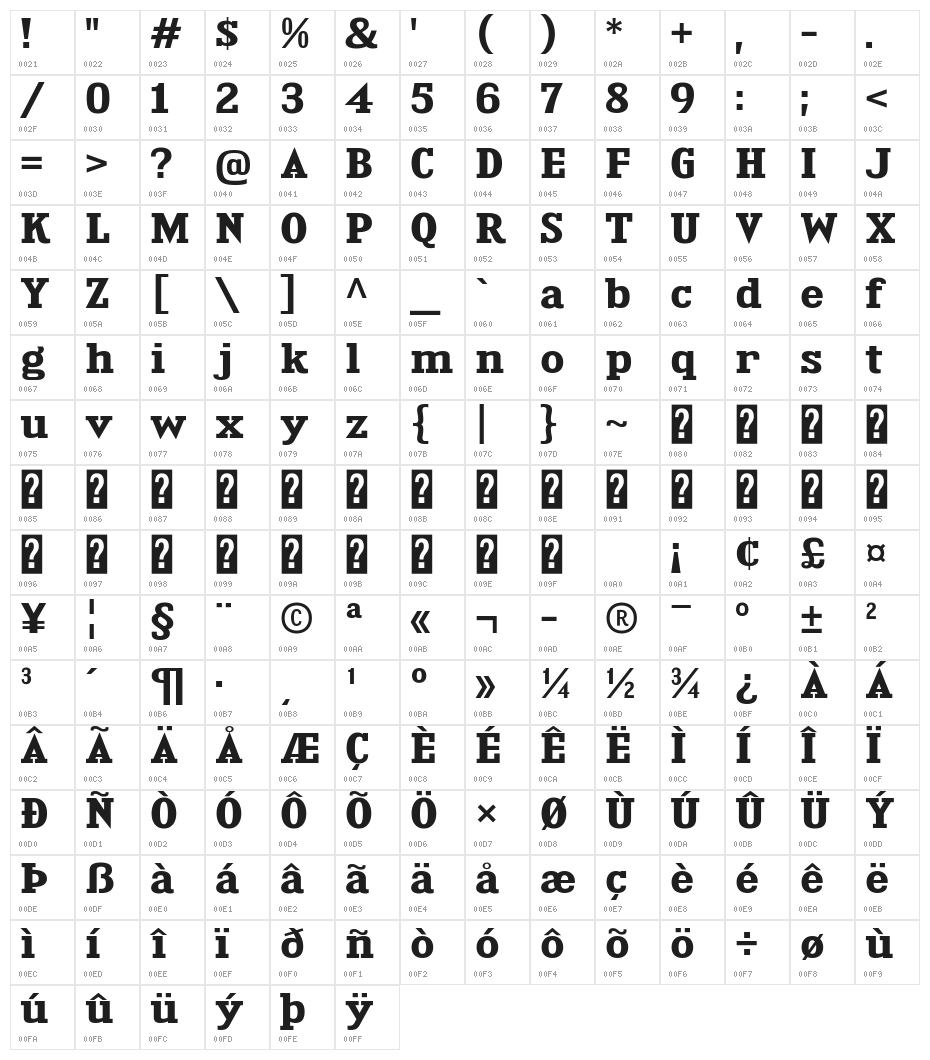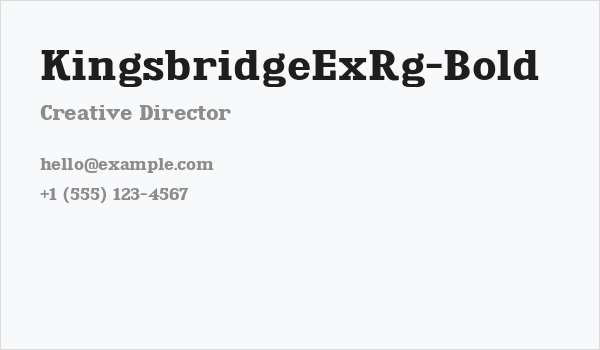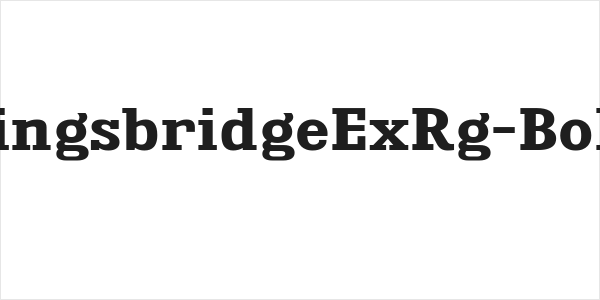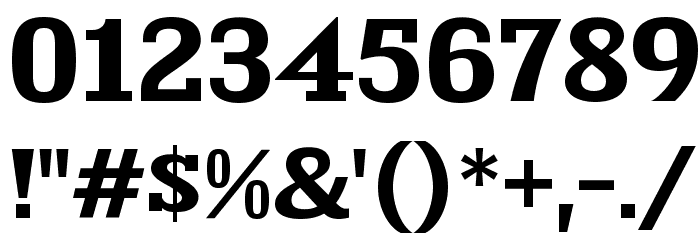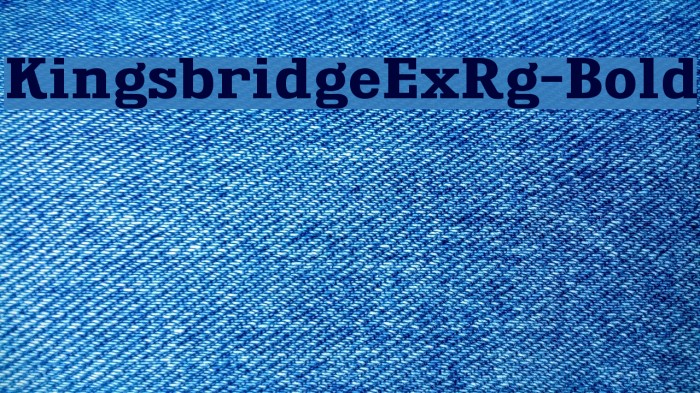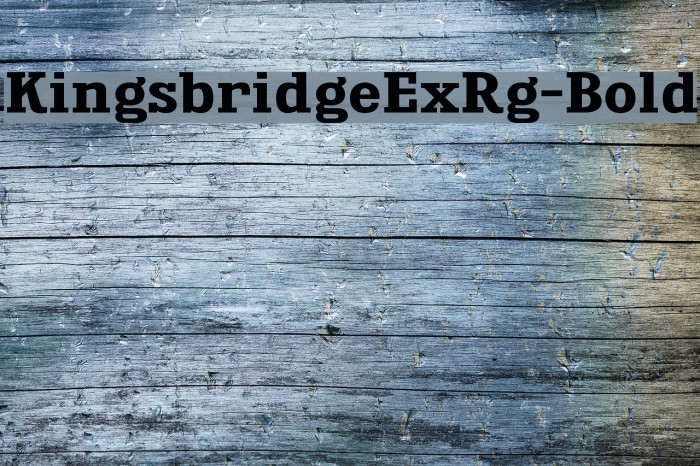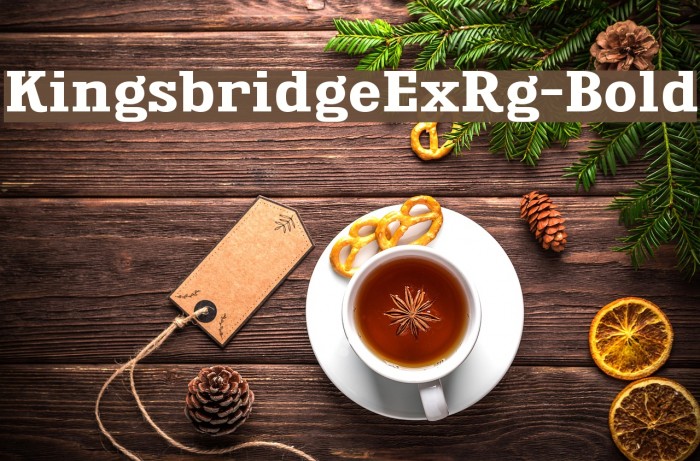
KingsbridgeExRg-Bold Font
✎ Serif
Fonts by Typodermic Fonts
| Caso de uso | Headlines, Logos, Branding |
| Proyectos propuestos | This font is perfect for projects that require a strong visual impact, such as branding, advertising, headlines, and editorial design. Its bold nature makes it suitable for logos and packaging where readability and presence are key. |